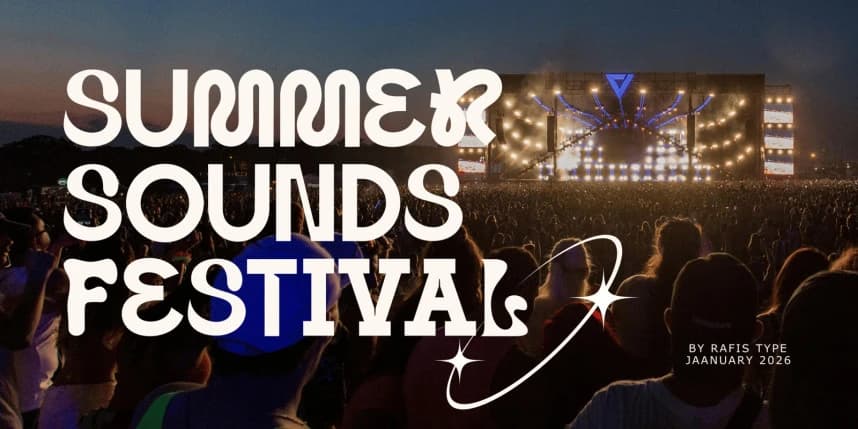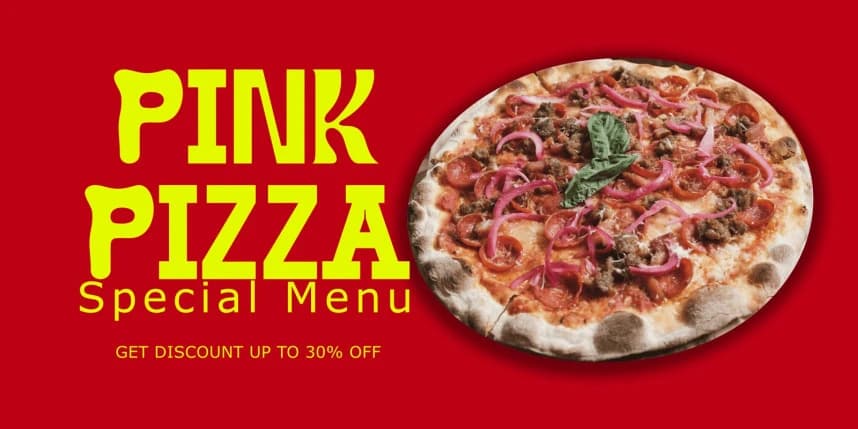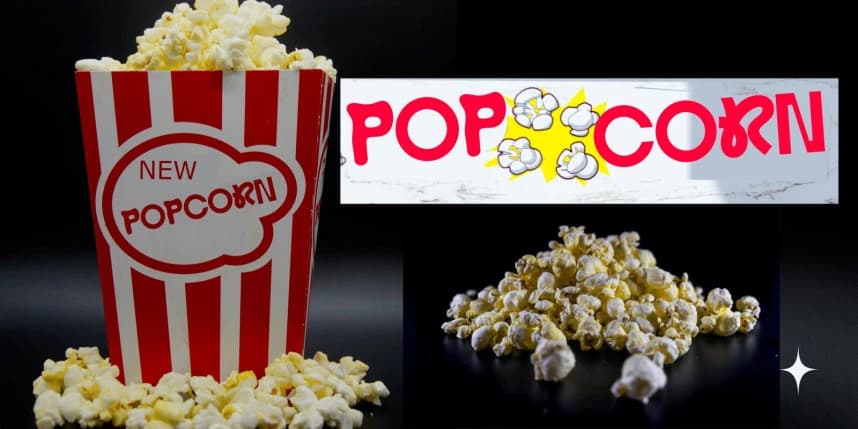
Mecsicola Yazı Tipi
Mecsicola Font, benzersiz ve ifade gücü yüksek bir karaktere sahip bir gösteri yazı tipidir; modern bir retro hava ile oyunlu bir dokunuştan ilham alır. Harf biçimleri cesur ama esnektir ve bu da güçlü, yaratıcı ve şık bir izlenim yaratır.
Mecsicola Font, benzersiz ve ifade gücü yüksek bir karaktere sahip bir gösterim yazı tipidir; modern bir retro hava ile oyuncu bir dokunuştan esinlenmiştir. Harf biçimleri cesur fakat esnektir; güçlü, yaratıcı ve şık bir izlenim yaratır.